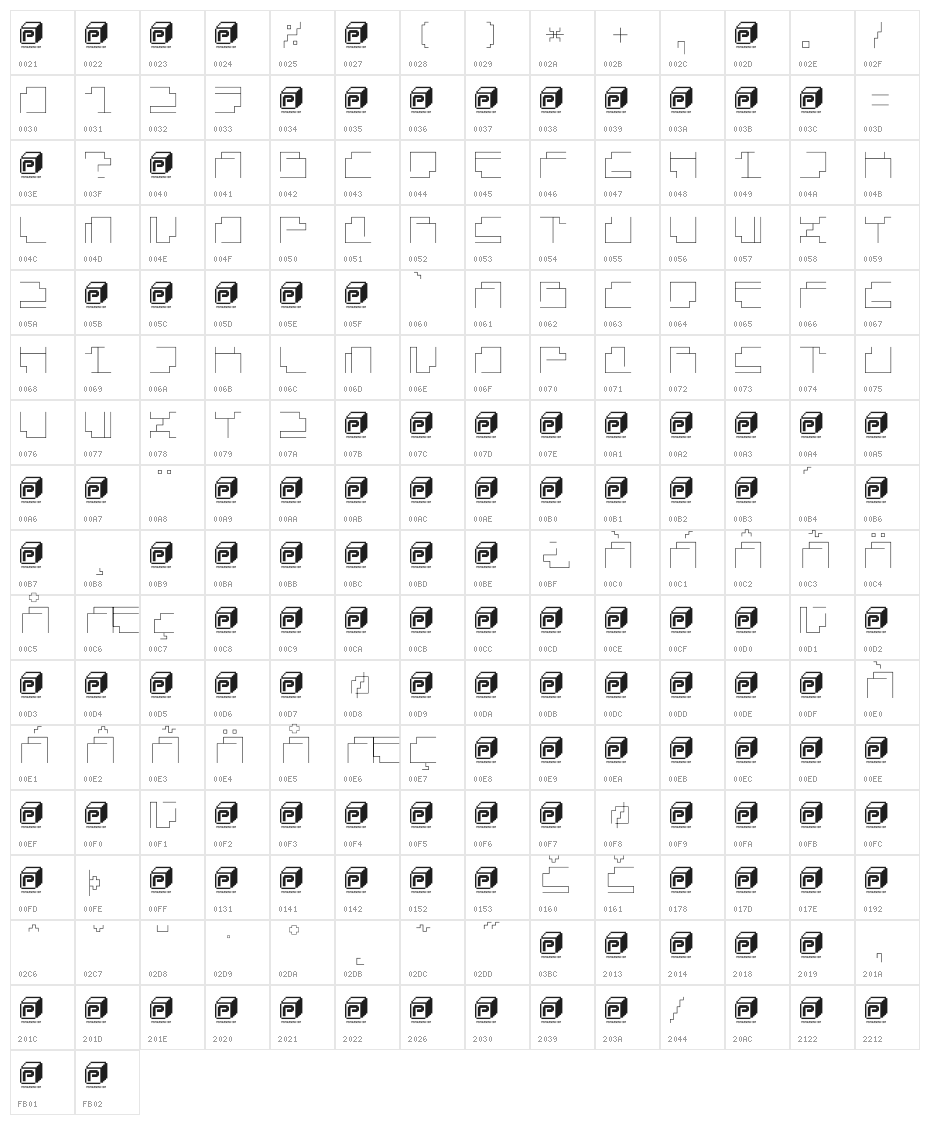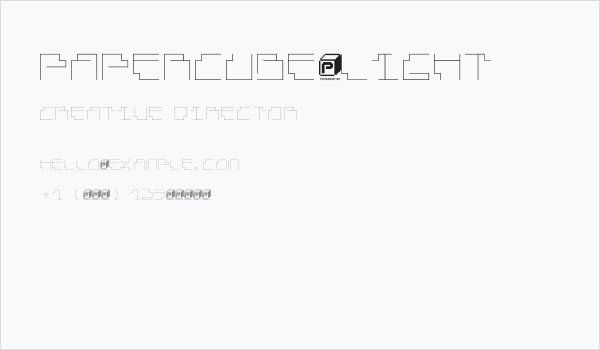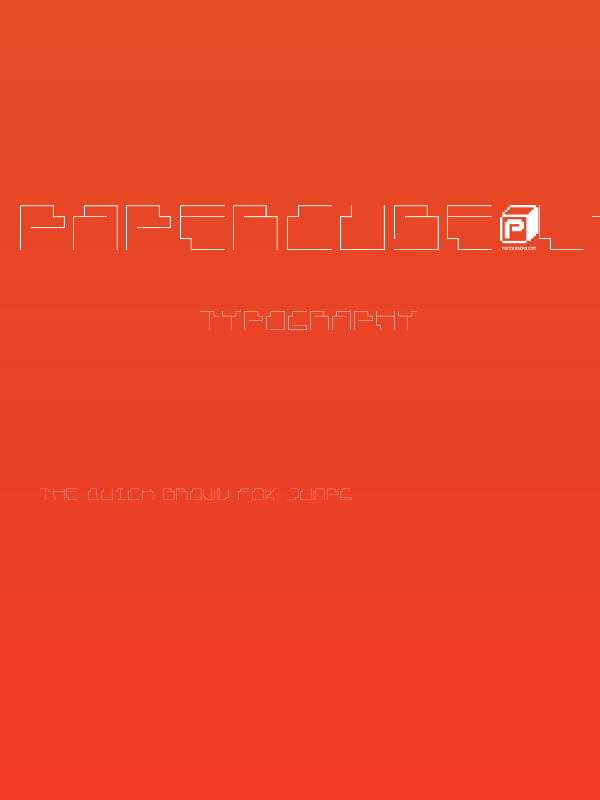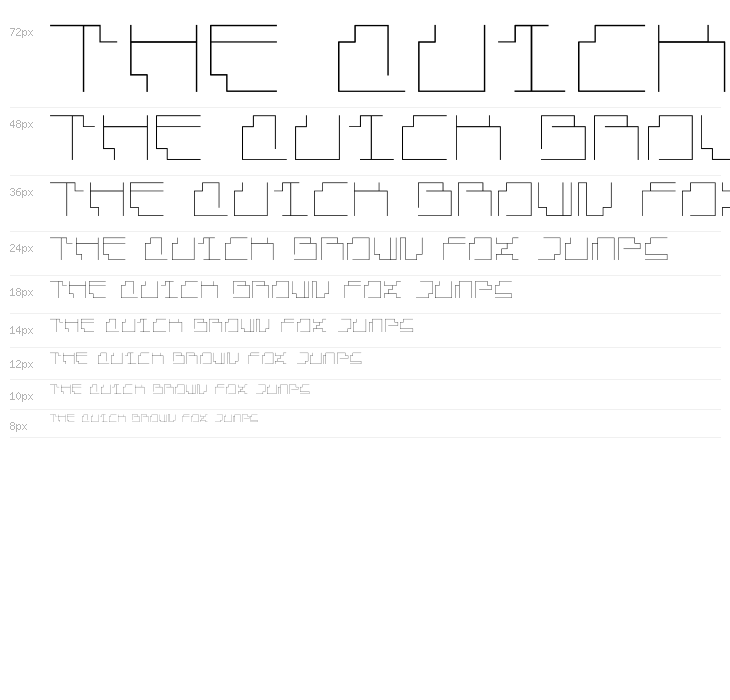
PaperCube-Light Font
| Caso d'uso | Logos, Headlines, Digital Art |
| Progetti proposti | Ideal for tech branding, digital art, futuristic posters, and modern web design. |